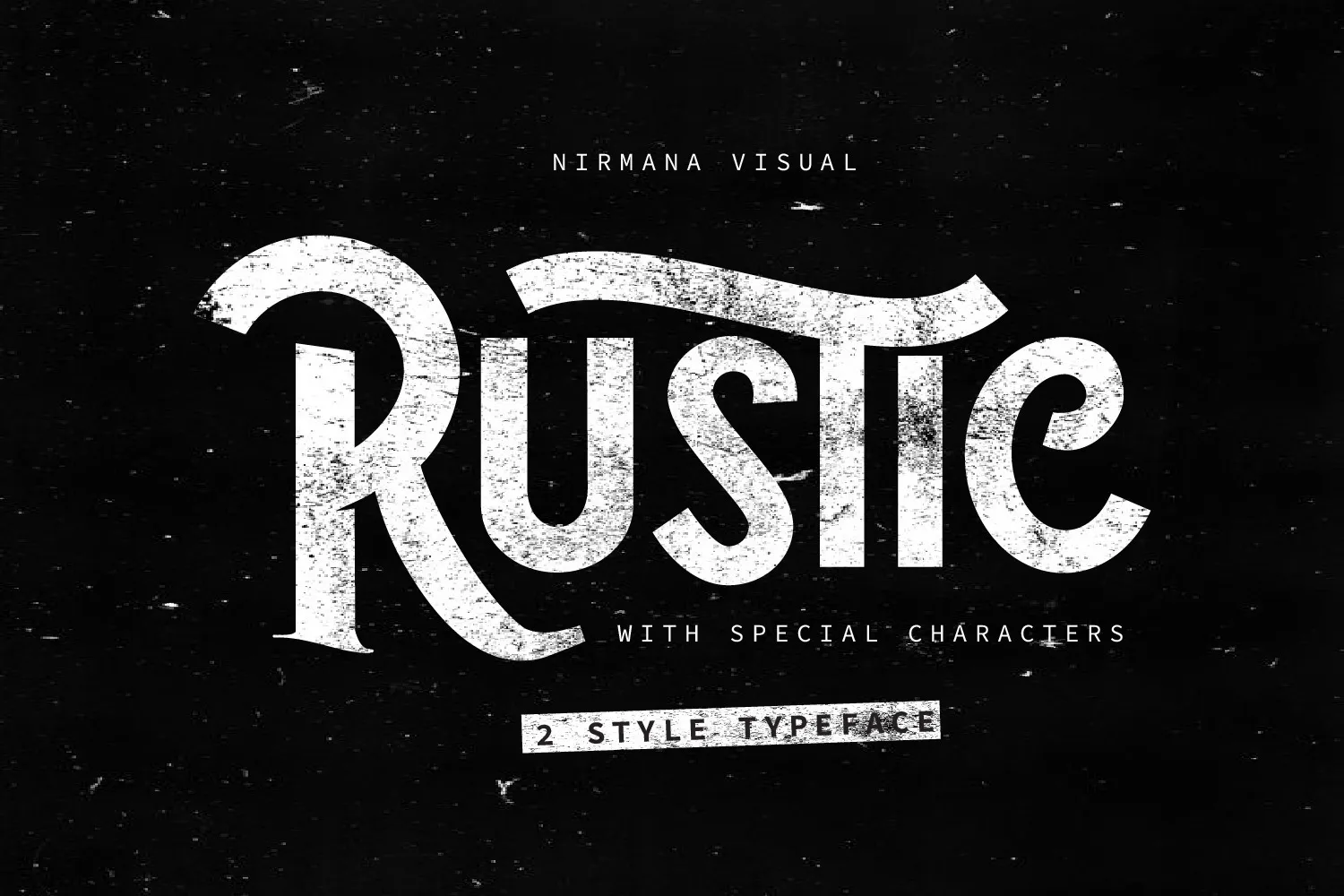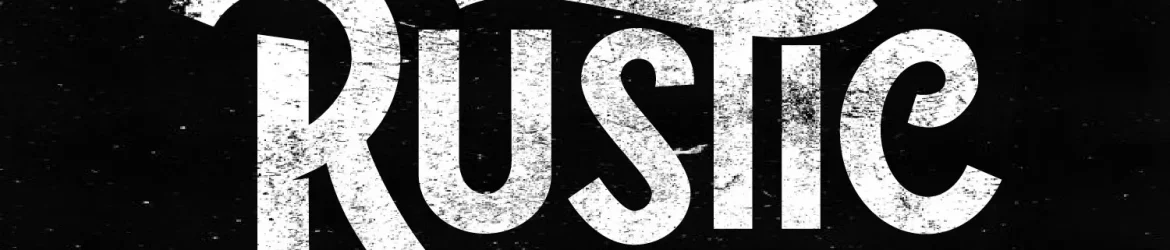
Introduzimos The Rustic Typeface! Essa fonte romântica retrata a simplicidade das antigas fazendas e casas rústicas dos Estados Unidos, com linhas finas que remetem ao pano de seda usado por esses ambientes. Com uma tipografia alternativa especial para caracteres especiais, The Rustic Typeface oferece um toque único à sua próxima produção gráfica ou projeto de web. Desenvolvida pelo designer Nirmana Visual, esta fonte retrata perfeitamente a atmosfera confortável e acolhedora dos ambientes rústicos do passado, tornando-a uma escolha ideal para design retro e moderno.